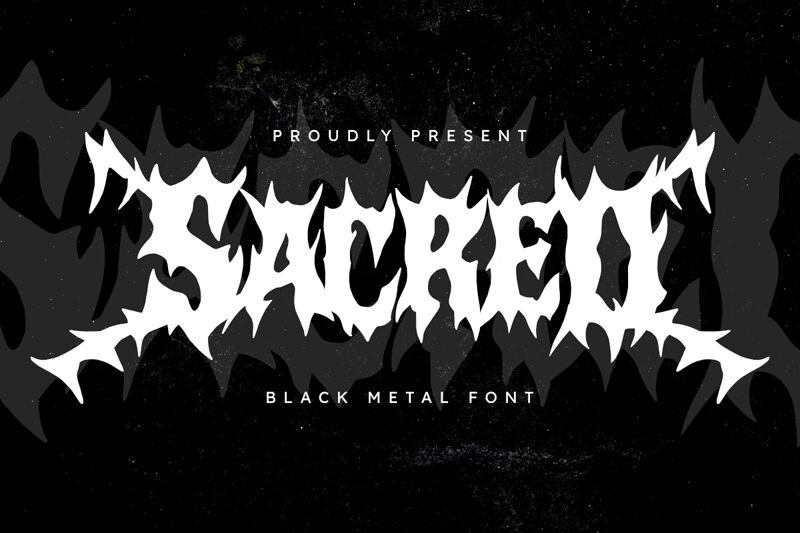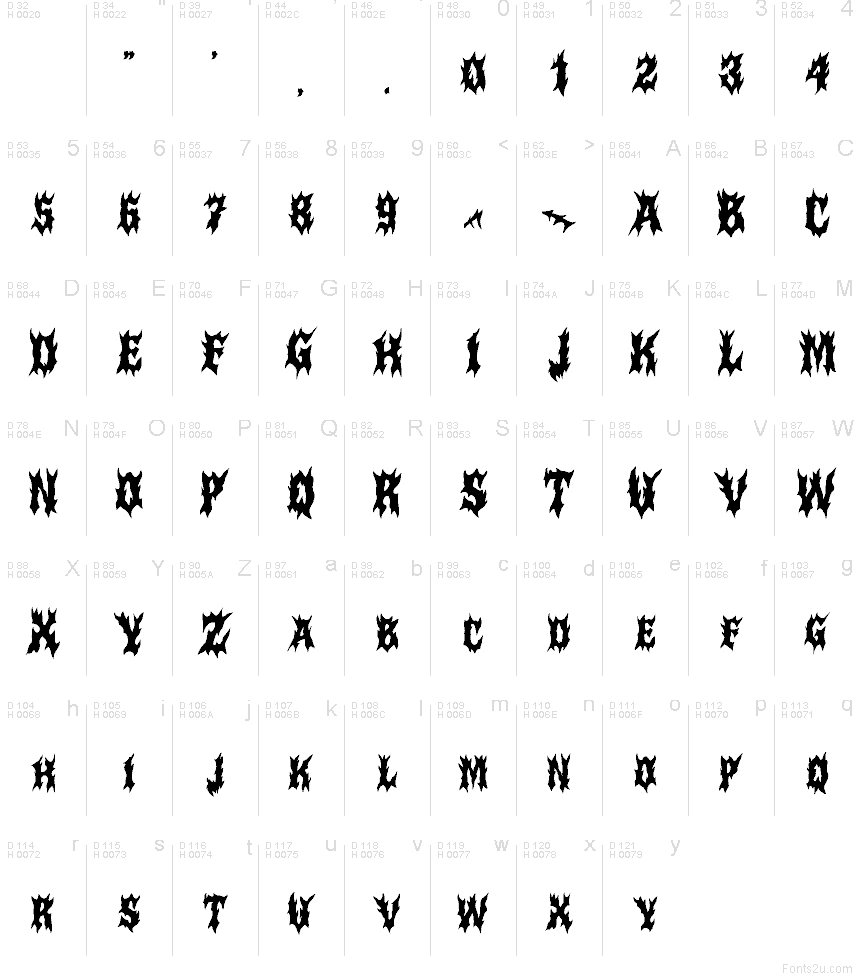
Sacred od Masyafi Studio je bezplatné gotické písmo s rozeklanými tvary připomínajícími plameny a hrubými, špičatými okraji. Tvary působí dojmem vytesání, s výraznými otvory a hlubokými zářezy, které dodávají nápisům temný a ručně kreslený vzhled.
Sacred skvěle funguje na obalech alb, plakátech k hororům, v návrzích tetování, metalovém brandingu, názvech her a letácích, protože jeho ostré tvary mají v krátkých textech silnou a dramatickou působivost. Toto bezplatné písmo se hodí také pro loga a nadpisy, u nichž je vyžadován surový, přímý a dravý gotický styl.